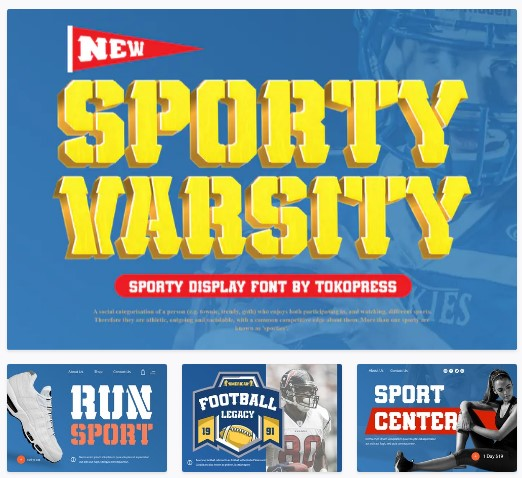
Название: Sporty Varsity Font (2021)
Sporty Varsity - трафаретный шрифт
Пот, веселье, гол, очки.... и чемпион в процессе становления. Sporty Varsity даст полную энергию вашему проекту на полном газу.
Отлично подойдет для спортивной аудитории игрового рынка, гоночного плаката, названия фильма, журнала, обложек youtube, миниатюр youtube, обложек страниц социальных сетей и так далее...
Основные латинские буквы A-Z и a-z, цифры, пунктуация